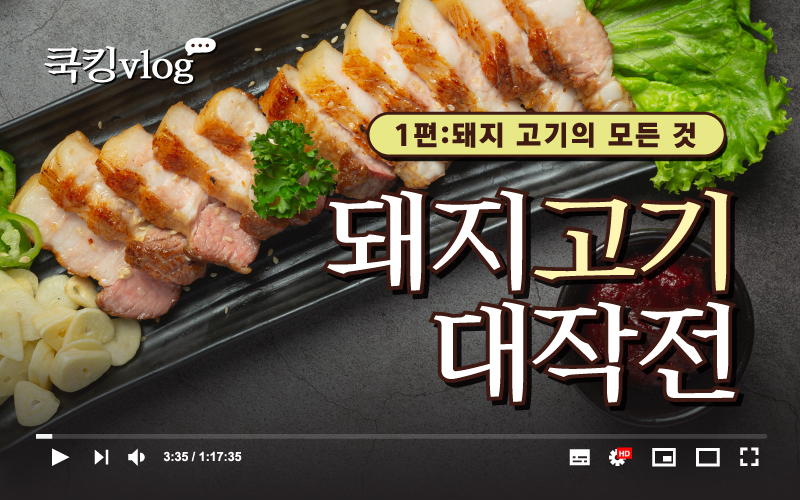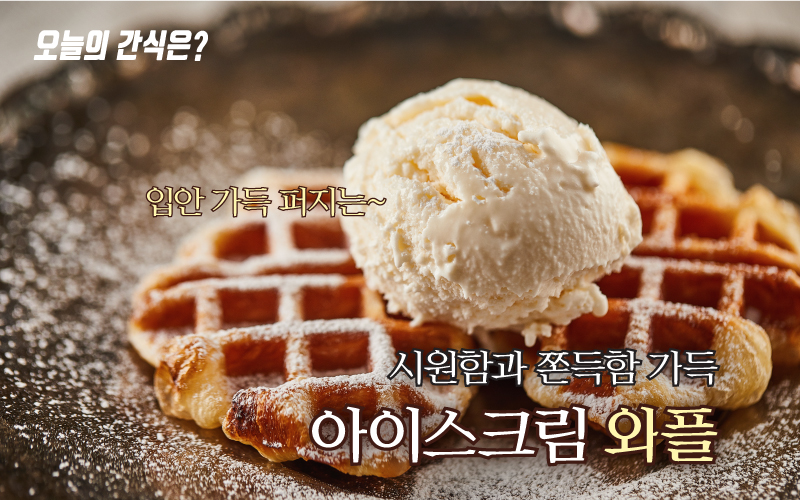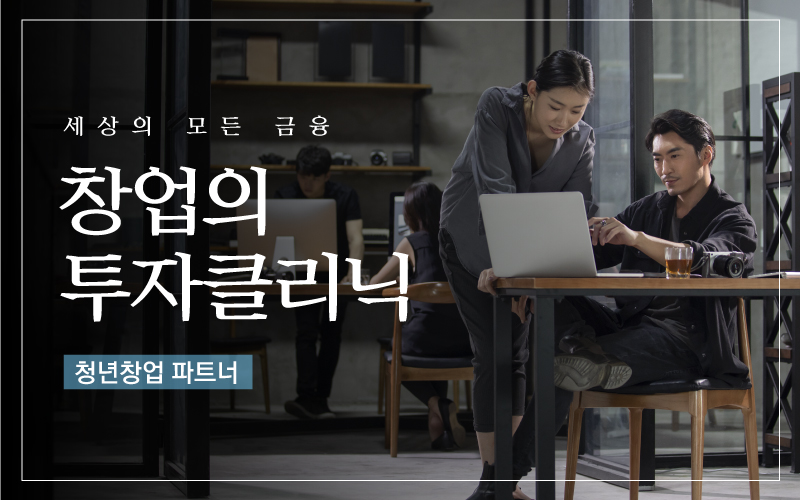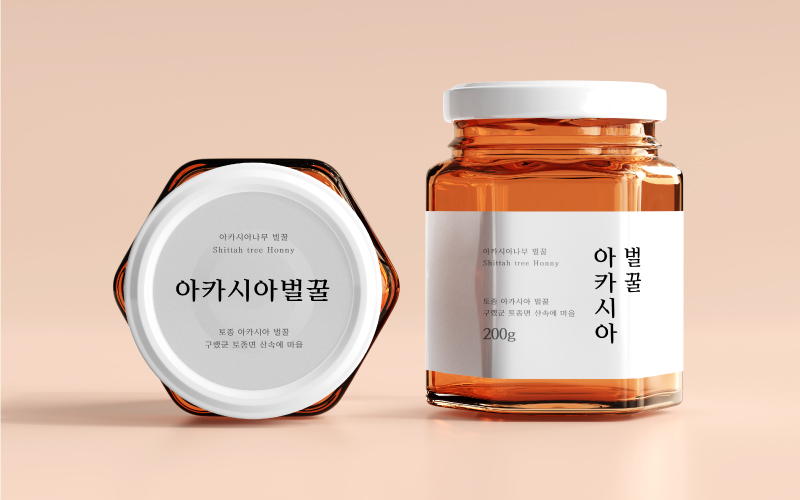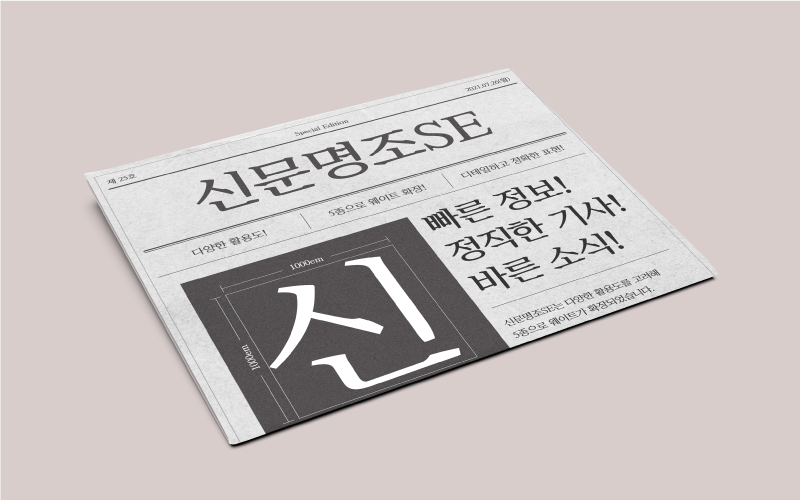
Rix신문명조SE는 여유로운 공간감과 높은 가독성을 가진 서체 신문명조의 Special Edition입니다.
더 세분화된 굵기의 5가지 웨이트와 라틴 문자 영역 확장으로 사용성을 높였습니다.
트렌디한 넓은 가로폭의 명조체로 방송 자막, 타이틀 등 다방면에 활용하기 좋습니다.